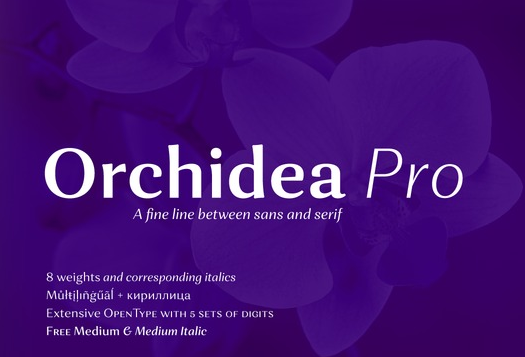
Introduzimos a nova família de fuentes: Orchidea Pro Font Family, criada pelo designer Hamilton. Esta é uma tipografia que flutua entre serif e sans-serif. Trata-se de um “sans-serif com serifas” ou “tipo sem serifas sem serifs”, pois não contém sinais finos nos cantos dos caracteres como ver em outras fuentes sans-serif, mas as formares do tipo parecem serifados e tem formas pontiagudas que aceleram a leitura, criando uma característica única. Essa tipografia é ideal para situações onde você deseja um aspecto moderno sem perder o aspecto de serifas tradicionais, tornando-a perfeita para o layout digital atual. Esta família de fuentes combina facilmente com qualquer fonte serif ou sans-serif, e a sua qualidade garante que a legibilidade se mantém mesmo em grandes tamanhos. O Orchidea Pro é uma ótima escolha para designers gráficos que procuram um toque moderno e distinto em seus projetos.